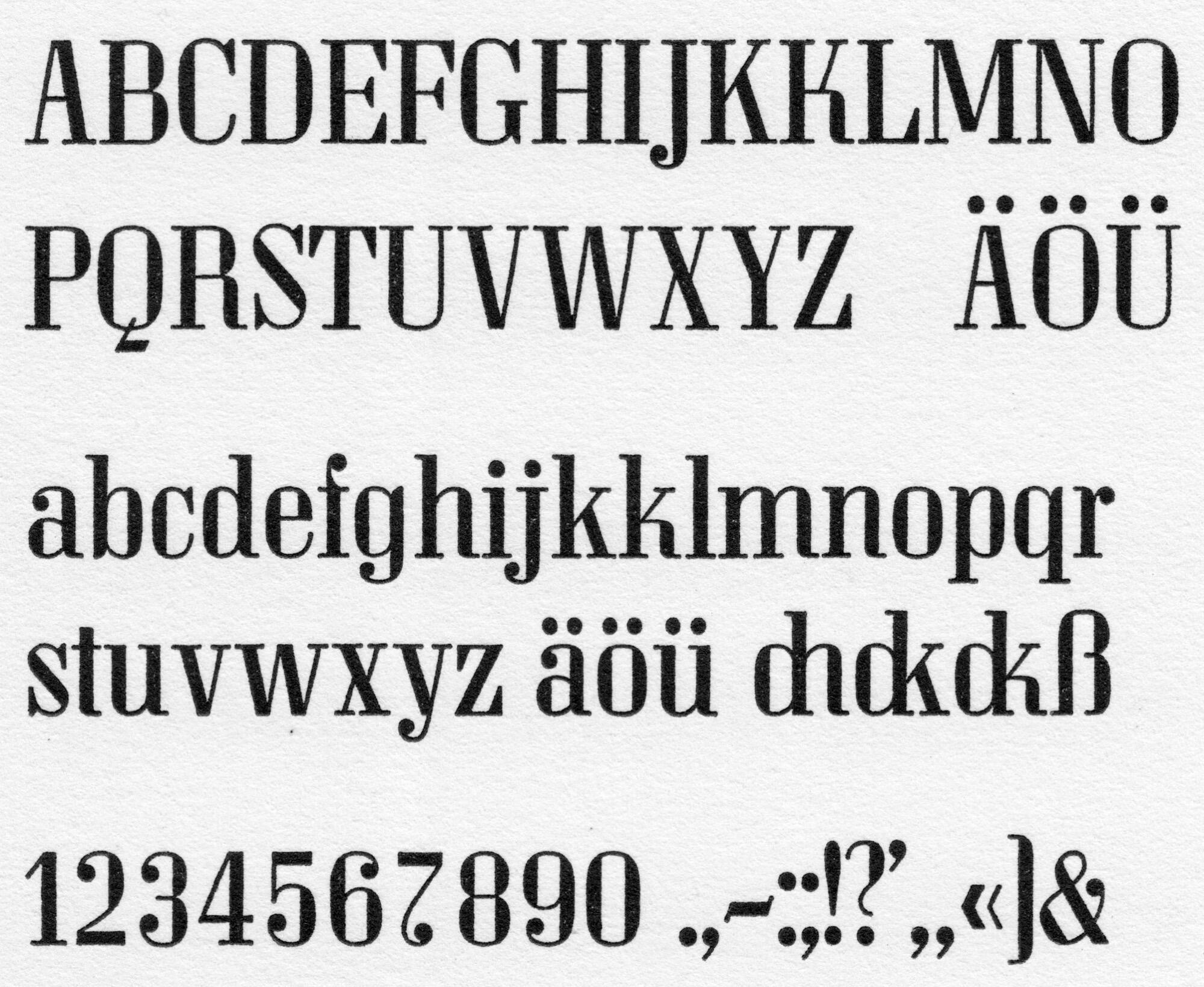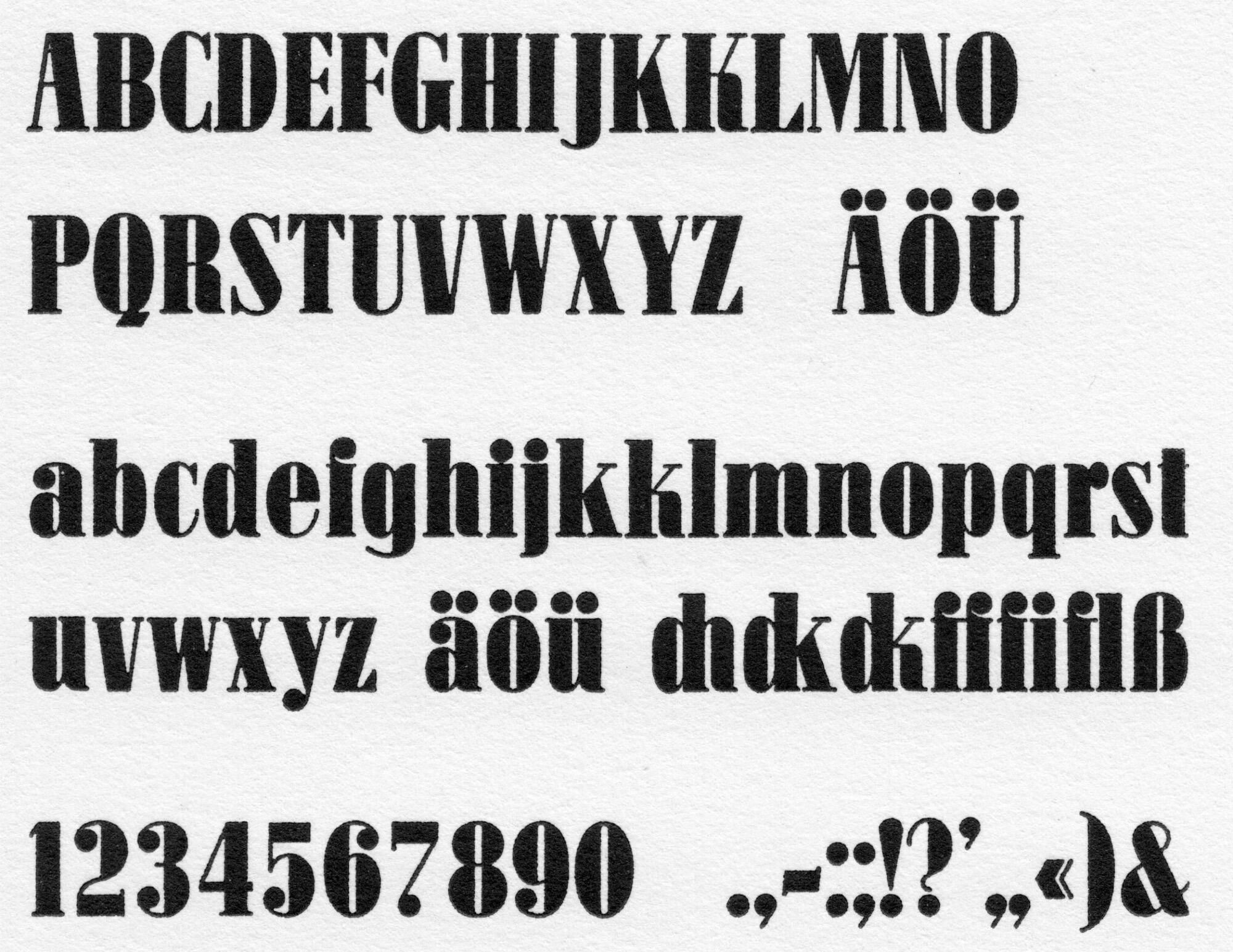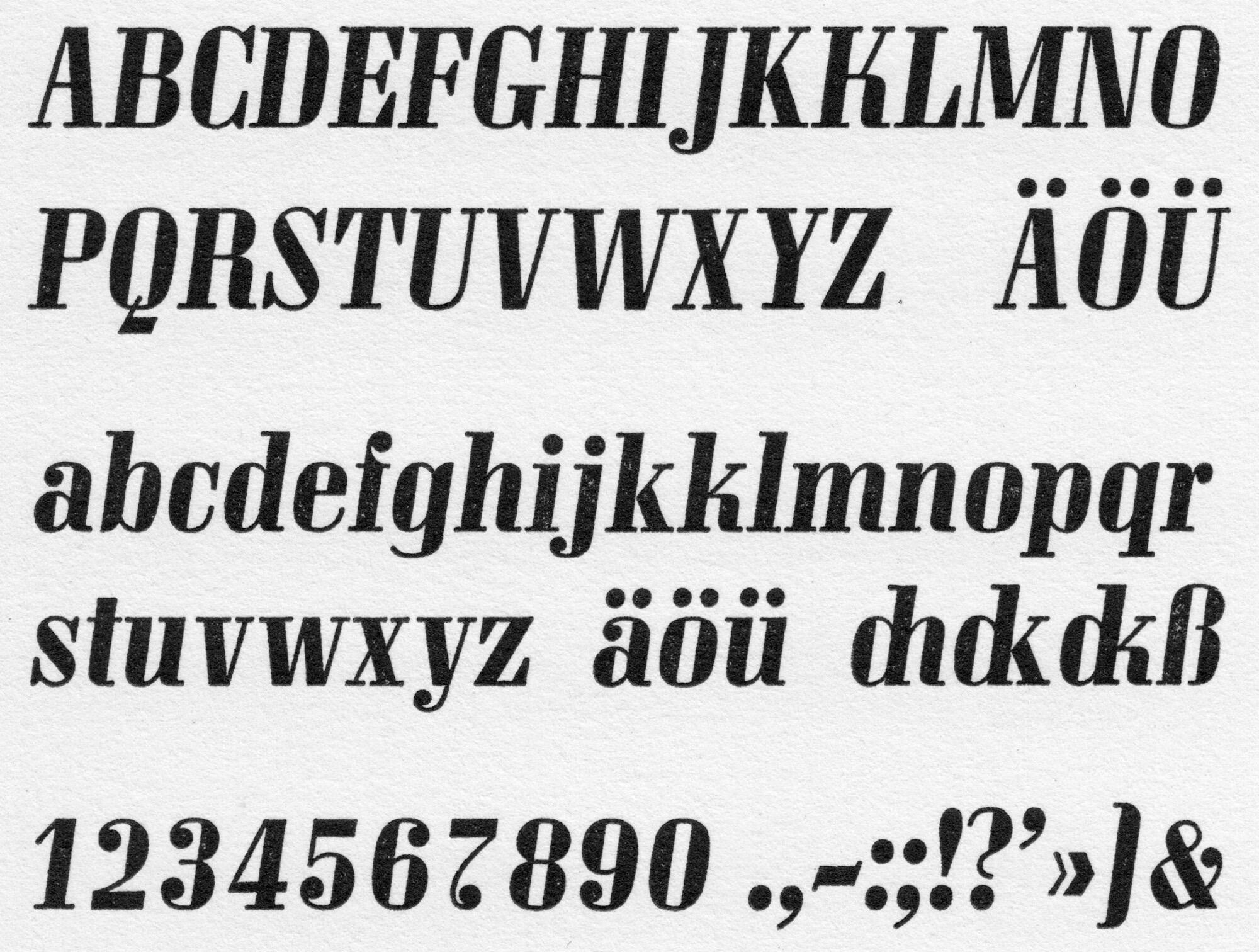
• 1936
• Serifen:
• serif
• Antiqua statisch
Die Mondial von Hans Bohn erschien ab 1936 als der »neue Typ der Klassischen Antiqua« bei der D. Stempel AG. Zur Familie zählen zwei Strichstärken (mager/halbfett) mit Kursiven sowie ein schmalfetter Schnitt mit einer zusätzlichen »Hoch«-Variante mit verlängerten Oberlängen. 1939 wurde als letzte Erweiterung ein fetter Schnitt hinzugefügt.
Eine moderne Interpretation gibt es als Mondial Text und Mondial Display von Revolver Type.